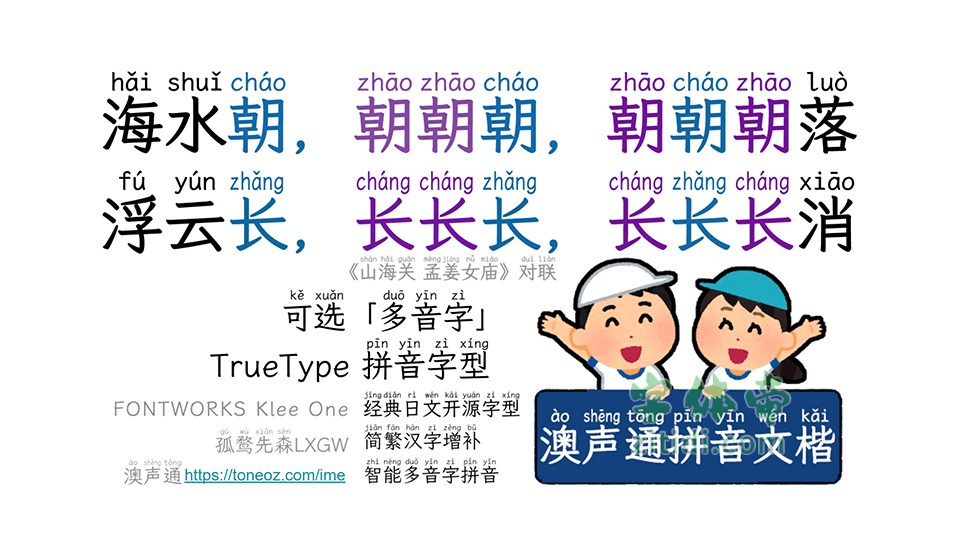
澳声通拼音文楷是一款基于克利Klee One以及霞鹜文楷的制作中文字体,可以搭配免费免安装在线多音字选音工具澳声通使用。「表意文字变体多音字选择器」的概念来自But Ko的「注音IVS字型规格」。
多音字的使用方式是:先在选音编辑器打字,此编辑器会在瞬间自动帮你选择正确拼音,也可手动校正。完成后再将整段纯文字(已内嵌拼音信息)复制贴上到 Office,能省下大量排版及破音字校正的时间。贴到Office后再将字型选成「澳声通拼音文楷」便可看到正确多音字的拼音。
“澳声通拼音文楷”是一款书写很新颖的字体,字体大方,适合各种设计作品使用!欢迎下载!